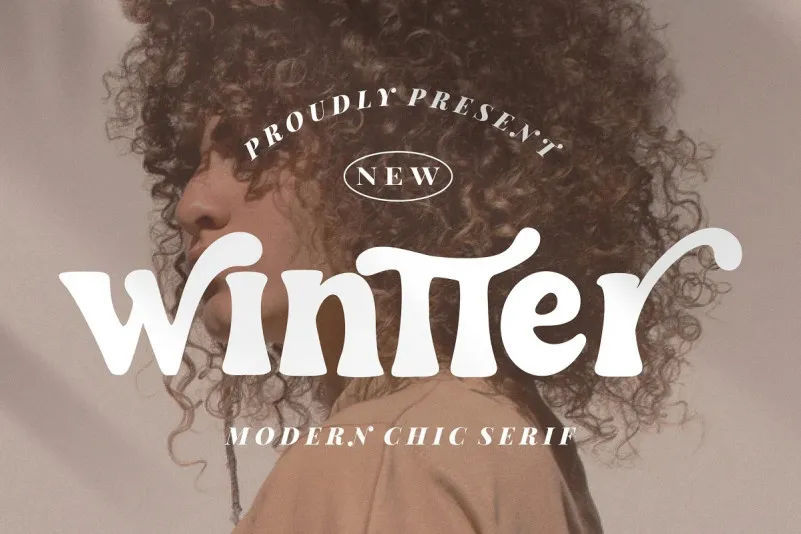
A fonte Wintter é perfeita para projetos que buscam uma atmosfera nostálgica e sofisticada. Com seu estilo retro, ela se destaca como a escolha ideal para trabalhos de design gráfico, desde rótulos até embalagens de produtos, passando por assinaturas de marca e identidade visual de negócios. Seu aspecto elegante e cuidadosamente elaborado torna-a uma opção perfeita tanto para aplicações digitais quanto em materiais impressos finos, garantindo que sua escrita traga um toque delicado aos seus projetos. Independente do tipo de projeto, Wintter é a fonte certa para incorporar o charme das antigas tendências gráficas em seu design. A versatilidade da Wintter abrange desde assinaturas e etiquetas até postais de aniversário e material de embalagem, tornando-a uma escolha primordial para designers de produtos e marcas em busca de um toque especial em seus materiais impressos.